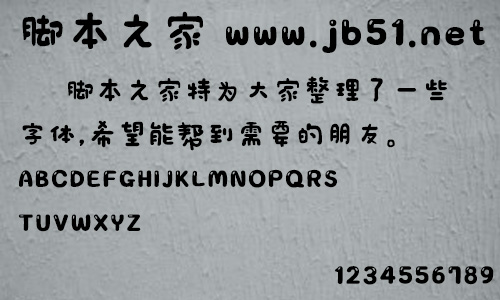
落落補(bǔ)湯圓體是一款最新的中文字體,這款字體筆觸較為粗實(shí),字體清晰明朗,字形圓潤(rùn)可愛,適合應(yīng)用于藝術(shù)設(shè)計(jì)、平面宣傳設(shè)計(jì)、網(wǎng)頁設(shè)計(jì),書法字體等領(lǐng)域,需要的朋友可以前來本站下載。